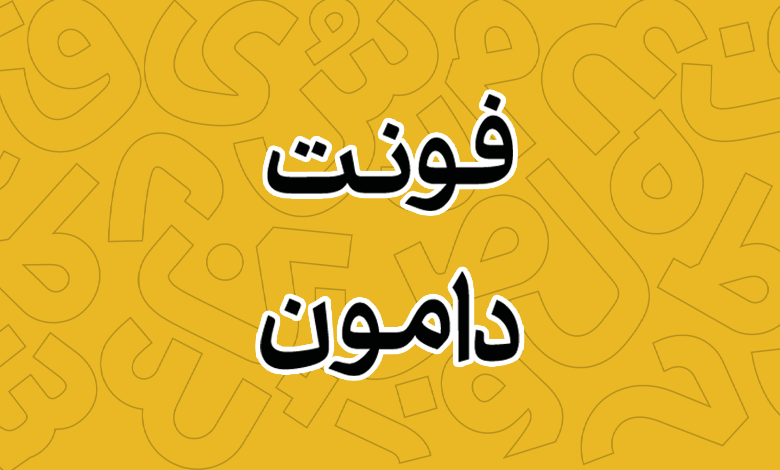
فونت دامون (Damoon)
فونت دامون (به انگلیسی: Damoon) قلمی مناسب تبلیغات و مطبوعات است که بر اساس خط نسخ طراحی شده است. این فونت را که میتوان یکی از متنوعترین فونتهای فارسی برشمرد، در مجموع از ۲۰ وزن پشتیبانی میکند که برای استفاده در متون طولانی، تنوع بالایی را در اختیار قرار میدهد.
طراح این فونت فارسی دامون خانجانزاده است که این فونت را با ایده نقاط حک شده روی ساطور قصابی طراحی کرده است. توسعه نرمافزاری این فونت نیز توسط رضا بهلول انجام گرفته است. در ادامه با نقد و بررسی فونت دامون با شما همراه هستیم.
فونت دامون به سبک نسخ طراحی شده، اما برخلاف نسخهای سنتی، خطوط تیز و فرمهای جسورانهای در وزنهای پایین دارد که آن را برای طراحی مدرن مناسب میکند. در مقابل هرچه وزن فونت افزایش مییابد این تیزی همچون کند شدن ساطور قصابی، کاهش مییابد.
ترکیبی از ظرافت خوشنویسی و استحکام فرمهای مدرن، باعث شده که این فونت هویتی منحصربهفرد داشته باشد. الهامگیری از ترکیب خوشنویسی و فرمهای صنعتی (مانند ساطور قصابی) نشاندهنده نگاهی نو در طراحی حروف فارسی است.
با توجه به ویژگیهای وزنی گسترده از Hairline تا Heavy، این فونت هم برای متون بلند مثل مقالات و هم برای عناوین و تیترها کاربرد دارد. در وزنهای سنگین، فونت حالتی استوار و محکم به خود میگیرد که برای تبلیغات و طراحی پوستر مناسب است، درحالیکه وزنهای نازک آن، حس ظرافت و مینیمالیسم را القا میکند.
پشتیبانی از ۵ زبان متنوع
فونت دامون از زبانهای فارسی، عربی، کردی، اردو و انگلیسی پشتیبانی میکند. این ویژگی باعث شده که دامون یک گزینه عالی برای برندهایی باشد که در کشورهای فارسیزبان و عربیزبان فعالیت میکنند. همچنین، وجود حروف جایگزین و اعداد فارسی، انعطاف بیشتری برای استفاده در پروژههای متنوع ایجاد میکند.
در بخش حروف شاهد پیادهسازی استاندارد گلیفهای اعداد برای همه زبانها هستیم؛ بهطوری که اعداد متفاوت عربی «۰۴۵۶» ظاهر خود را متمایز از اعداد فارسی دارند. همچنین در بسته دانلود فونت دامون برای اینکه به شکل حرفهای از اعداد در وب استفاده کنید، نسخه مخصوص اعداد فارسی هک شده قرار گرفته است.
دارای حروف جایگزین و گلیفهای خاص
این فونت دارای صدها ترکیب دو و سهحرفی است که باعث میشود متن در هنگام تایپ، ظاهری پویا و متنوع داشته باشد. با توجه به پشتیبانی از نسخه وریبل نیز ویژگیهایی مانند فارسیسازی اعداد، تنظیم تراز عمودی، گلیفهای ریال و تومان فشرده، این فونت را برای استفاده در طراحی رابط کاربری، نشر دیجیتال و تبلیغات ایدهآل میکند.
ترکیبات جایگزین به شما این امکان را میدهد تا بتوانید کلمات خاصی را با ظاهری متفاوت تایپ کنید. این موضوع در مبحث تبلیغات بسیار روی جذب نگاه مخاطب تاثیر خواهد داشت که نرخ نمایش را بالاتر میبرد. علاوه بر این زیبایی کار شما را دوچندان خواهد کرد.
با توجه به ویژگیهای ذکرشده، فونت دامون میتواند در موارد زیر کاربرد داشته باشد:
- مطبوعات و روزنامهها (به دلیل خوانایی بالا).
- برندینگ و هویت بصری (به دلیل سبک مدرن و فرمهای قوی).
- تبلیغات و طراحی پوستر (به دلیل تنوع وزنی و ترکیبات پویا).
- رابطهای کاربری و وبسایتها (به دلیل قابلیتهای تایپوگرافی).